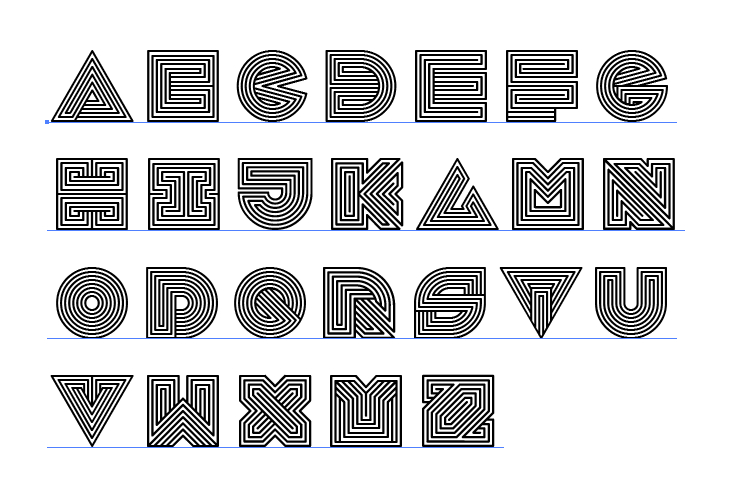
近日在整理舊文檔時,發現了藏在角落裡的一個字體設計文件,2012年做的一套英文字體,當時發表在站酷,近日我又整理了一下,變成了可以安裝在電腦裡的字體包。
由於當時只設計了26個字母,所以安裝到電腦後,無論輸入大寫小寫都只顯示大寫,沒有標點符號數字,更沒有中文。字體建議適用人群:設計師,設計愛好者,設計專業學生。